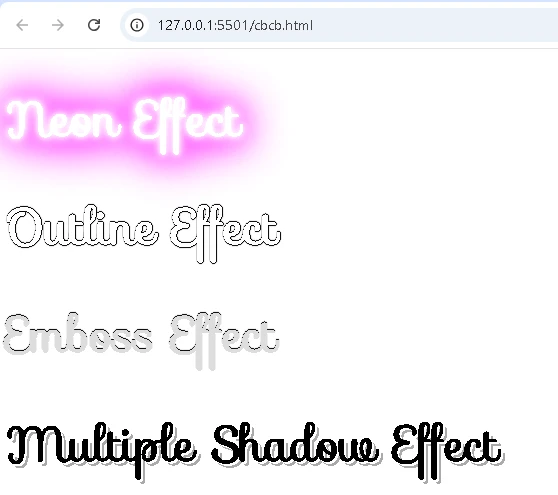
1. Font Style (Gaya Tulisan)
Properti font-style
digunakan untuk mengubah tampilan teks menjadi miring atau tetap normal.
Tersedia tiga pilihan:
normal
→ Teks tampil biasa (tidak miring).
italic
→ Teks ditampilkan dalam format miring (italics).
oblique
→ Teks juga miring, mirip dengan italic
, tetapi jarang digunakan dan tidak didukung di semua browser.
Contoh kode CSS:
p.normal {
font-style: normal;
}
p.italic {
font-style: italic;
}
p.oblique {
font-style: oblique;
}
berikut hasilnya
Ukuran Font dalam CSS (CSS Font Size)
Properti font-size
digunakan untuk mengatur ukuran teks pada halaman web.
Mengatur ukuran teks dengan baik sangat penting untuk desain yang nyaman dibaca.
Namun, jangan menggunakan ukuran font untuk menggantikan heading (<h1> - <h6>
) atau paragraf (<p>
). Sebaiknya gunakan elemen HTML yang sesuai agar struktur halaman tetap jelas.
1. Tipe Ukuran Font
Ada dua cara utama dalam menentukan ukuran teks:
A. Ukuran Absolut
Menentukan ukuran teks dalam satuan tetap (misalnya, px / piksel).
Tidak fleksibel, pengguna tidak bisa mengubah ukuran teks di beberapa browser.
Cocok digunakan jika ukuran tampilan sudah pasti, misalnya untuk desain cetak.
B. Ukuran Relatif
Mengatur ukuran teks berdasarkan elemen lain di sekitarnya.
Lebih fleksibel dan mendukung fitur zooming di browser.
Contoh satuan relatif: em, %, vw (viewport width).
Catatan: Jika ukuran font tidak ditentukan, browser biasanya menggunakan ukuran default 16px (1em = 16px).
2. Mengatur Ukuran Font dengan Piksel (px)
Menggunakan piksel (px
) memberi kendali penuh atas ukuran teks.
Contoh kode CSS:
h1 {
font-size: 40px;
}
h2 {
font-size: 30px;
}
p {
font-size: 14px;
}
berikut hasilnya
Google Fonts di CSS
Jika kamu ingin menggunakan font yang lebih menarik daripada font bawaan HTML, kamu bisa menggunakan Google Fonts.
Google Fonts adalah koleksi font gratis yang bisa digunakan di situs web, dengan lebih dari 1000 pilihan font.
Cara Menggunakan Google Fonts
Untuk menggunakan Google Fonts, cukup tambahkan link stylesheet di dalam tag <head>
lalu gunakan nama font tersebut di CSS.
Menggunakan Beberapa Efek Sekaligus
Gunakan pipe (|
) untuk menambahkan beberapa efek.
Contoh: Neon, Outline, Emboss, dan Shadow Multiple
<head>
<link rel="stylesheet" href="https://fonts.googleapis.com/css?family=Sofia&effect=neon|outline|emboss|shadow-multiple">
<style>
body {
font-family: "Sofia", sans-serif;
font-size: 30px;
}
</style>
</head>
<body>
<h1 class="font-effect-neon">Neon Effect</h1>
<h1 class="font-effect-outline">Outline Effect</h1>
<h1 class="font-effect-emboss">Emboss Effect</h1>
<h1 class="font-effect-shadow-multiple">Multiple Shadow Effect</h1>
</body>
berikut hasilnya